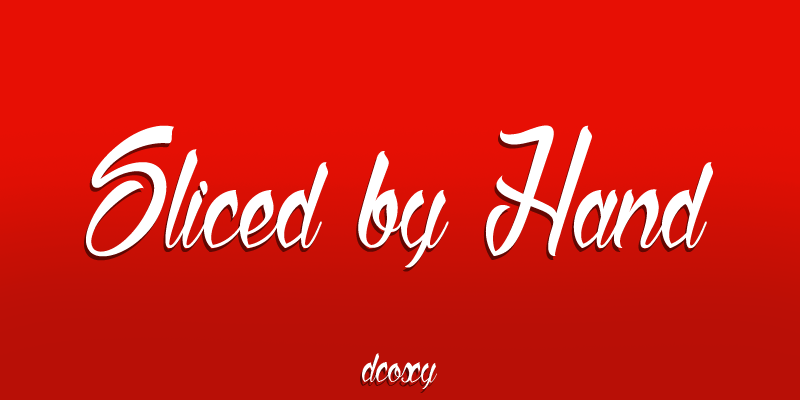
A fonte Sliced by Hand é uma criação meticulosa do designer Hamilton. Com suas linhas cuidadosamente cortadas e detalhes delicados, esta fonte se destaca como um recurso versátil para qualquer projeto que busque autenticidade e criatividade no seu tipo. Perfeita para trabalhos de arte, design editorial ou criação de materiais promocionais, a Sliced by Hand oferece uma combinação única de elegância e sofisticação. Seu uso não só é belo, mas também requer autorização para fins comerciais ou promocionais – por isso, antes de usá-la em qualquer projeto comercial ou que exija promoção, é sempre melhor entrar em contato com Hamilton através do email .